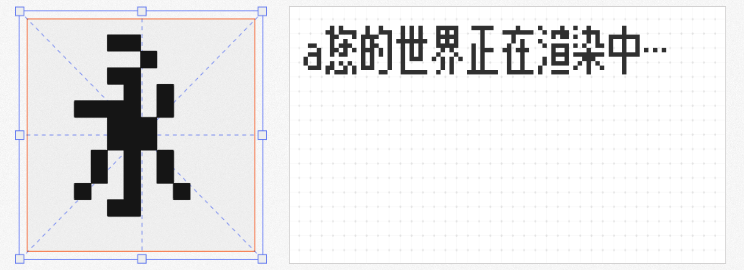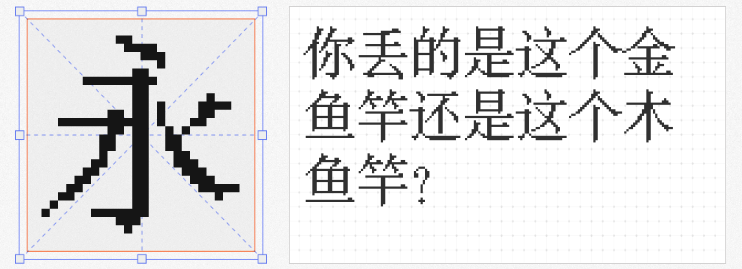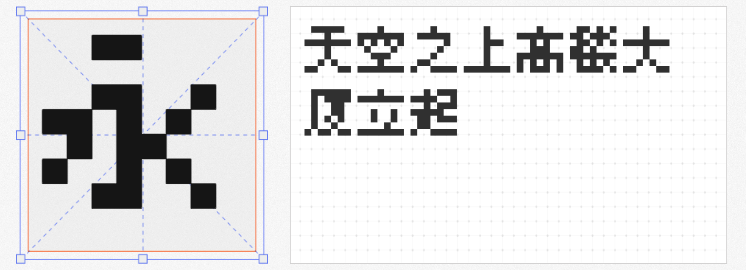
像素字体以独特的方格美学,在数字时代开辟出一条怀旧与未来交织的视觉路径。无论是打造赛博朋克风的科技感,还是复刻8-bit游戏的复古情怀,像素字体总能以精准的像素颗粒感,为设计注入灵魂。以下四款免费商用像素字体,兼具实用性与风格化表达,助你解锁设计的无限可能。
1. 寒蝉点阵体7px
作为「美咲フォント」与「精品點陣體7×7」的融合之作,寒蝉点阵体7px以7px的精巧像素尺寸,实现中英文字符的和谐共生。其字形在保留日式像素字体清冷质感的同时,通过调整英文部分与标点符号的细节,让整体视觉更显统一。适用于UI图标、电子设备界面或需要低分辨率美学的设计场景,在极简与个性间找到微妙平衡。
2. 美绩点阵体
以「最完整开源8x8点阵体」为定位,美绩点阵体凭借对多语言的支持(包括注音符号与国际音标),成为跨文化设计的理想选择。其8x8的方格矩阵既保留了早期电子设备的原始质感,又通过精密的像素排布确保文字可读性。无论是制作复古游戏海报、教育类可视化图表,还是作为科技风设计的点缀元素,这款字体都能以极简的像素语言传递信息。
3. 粗柳坊新24x
作为原始ChuLyu字体的替代品,粗柳坊新24x以宋体为骨架,将传统书法的笔触韵律转化为像素世界的几何秩序。24x的像素尺寸赋予字形更多细节表现力,使其在保持像素字体硬朗特质的同时,隐约透出宋体的文化底蕴。适用于文化类海报、书籍封面或需要融合传统与现代的设计项目,让像素美学承载更厚重的叙事。
4. 目哉像素体 Orig
基于经典k8x12字体改造的目哉像素体Orig,以8x12的像素矩阵构建出更丰富的字形结构。其中日文假名与中文汉字的像素化处理,既保留了日式像素字体的细腻感,又通过优化字形比例提升跨语言辨识度。这款字体尤其适合双语文案设计、复古风品牌周边或需要营造沉浸式像素世界观的场景,让每个字符都成为叙事像素。
像素字体的魅力,在于它能用最基础的数字方格,编织出跨越时空的视觉叙事。无论是致敬经典游戏,还是探索未来美学,这四款免费商用字体都能以独特的像素语言,为你的设计注入不可复制的灵魂。